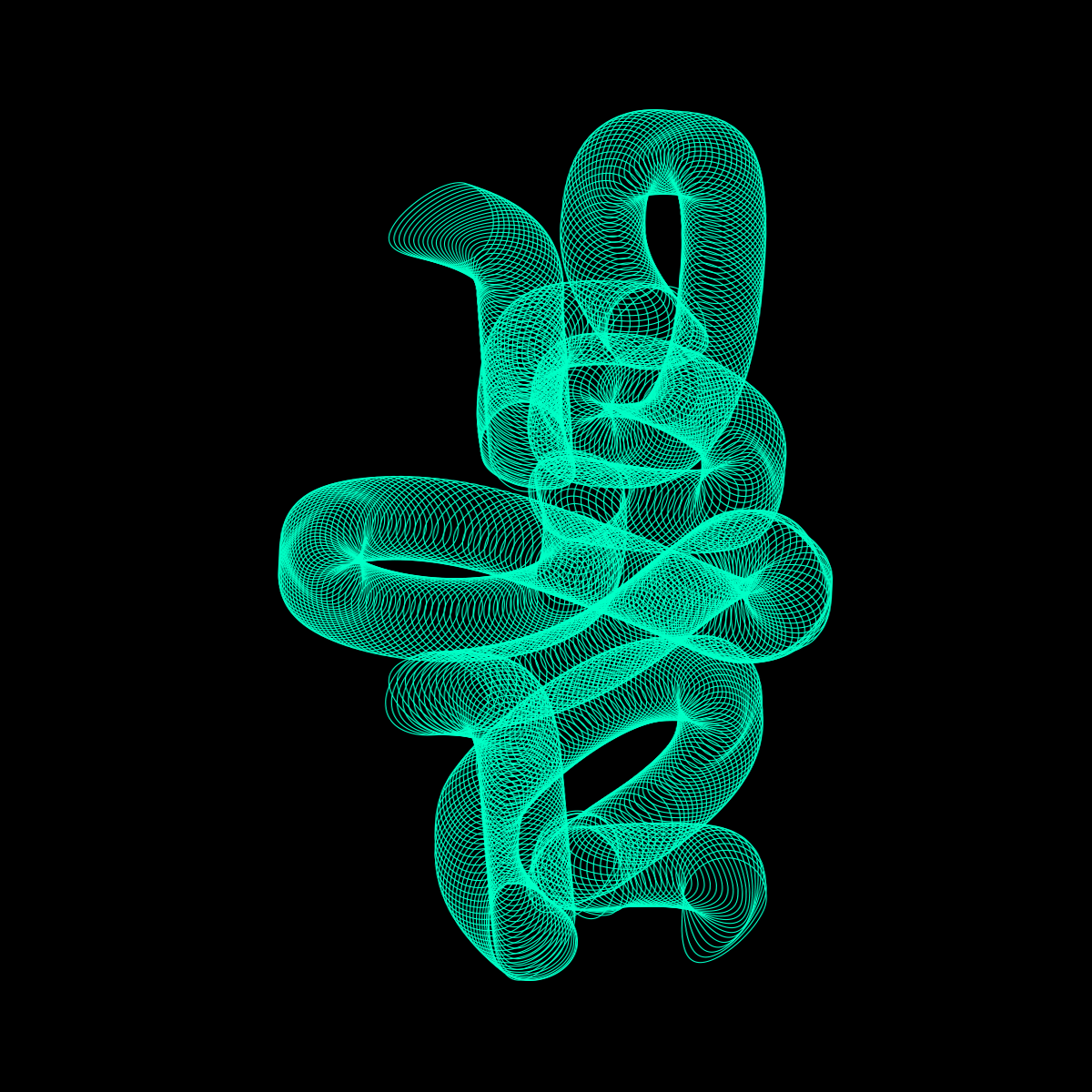
봄
ZESSTYPE LETTERING WORK 2017
기존 <봄> 레터링 작업에 블렌드 툴을 이용하여 표현에 변화를 주었습니다.
늘 비슷한 작업만 하다보니 점점 손에 익은 표현 방법만 사용하게 되는 것 같아서.
앞으로는 좀더 다양한 표현을 시도해 보고자 합니다.
글자의 형태와 글자의 표현. 최근 <개화> 프로젝트 관련 작업만 봐도 동일한 모듈로 작업하다보니 결과물이 죄다 비슷한 느낌이라서.
살짝 반성하면서 … 더 다채로운 작업들을 보여드릴 수 있도록.